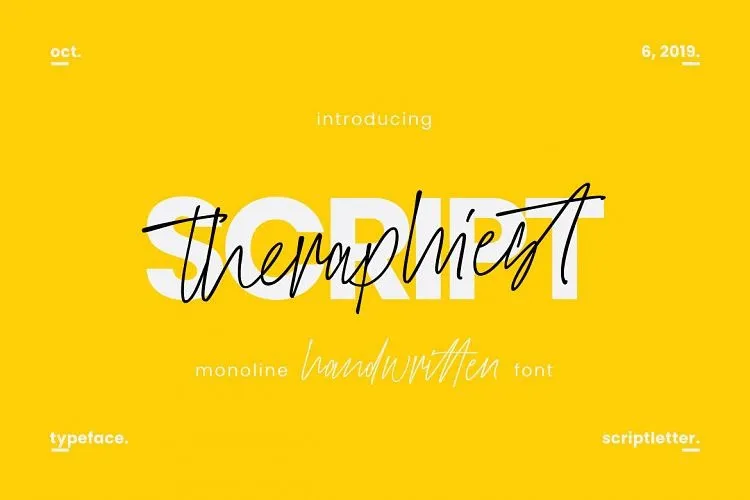
Theraphiest Script Font
Introduzimos a Theraphiest Font. Esta é uma nova tipografia em feitiço manuscrito que transforma seus textos num belo, luxuoso e contemporâneo estilo elegante. Este font foi projetado e compartilhado pelo Thirtypath. É um texto de mão escrita com o charme irregular do handwriting ainda assim elegantemente refinado. É perfeito para projetos de marca, design de móveis de casa ou embalagens de produtos – ou simplesmente como uma sobreposição estilizada ao fundo de qualquer imagem. Este font irá transformar a aparência de suas criações e dar um toque único à sua próxima obra de arte gráfica.